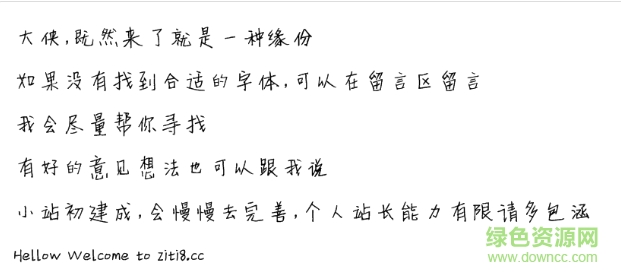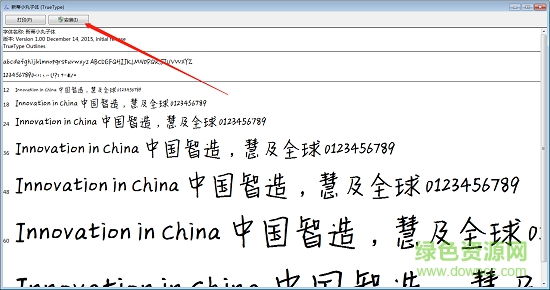
漢儀新蒂小丸子高級(jí)版字體是一款類似于手寫的字體,簡(jiǎn)單的筆畫中帶著一絲絲的可愛氣息,非常適合平時(shí)的卡片制作,同時(shí)用戶還能夠?qū)⒆煮w運(yùn)用到各種場(chǎng)合,喜歡的用戶快來(lái)綠色資源網(wǎng)下載吧!
漢儀新蒂小丸子體是一款非常可愛的字體,字體不是很規(guī)則,和孩子手寫似的,但是識(shí)別度卻很高,可以帶給人快樂的感覺,同時(shí)這個(gè)字體非常適合運(yùn)用到各種節(jié)日之中,用戶制作各種宣傳畫是再也適合不過(guò)了,快來(lái)使用看看吧!
1、支持簡(jiǎn)體中文。
2、支持西文和數(shù)字。
3、風(fēng)格:手寫、女性、優(yōu)雅、浪漫、溫柔、休閑、有趣、少女、快樂。
4、場(chǎng)景:廣告、游戲、動(dòng)漫、影視。